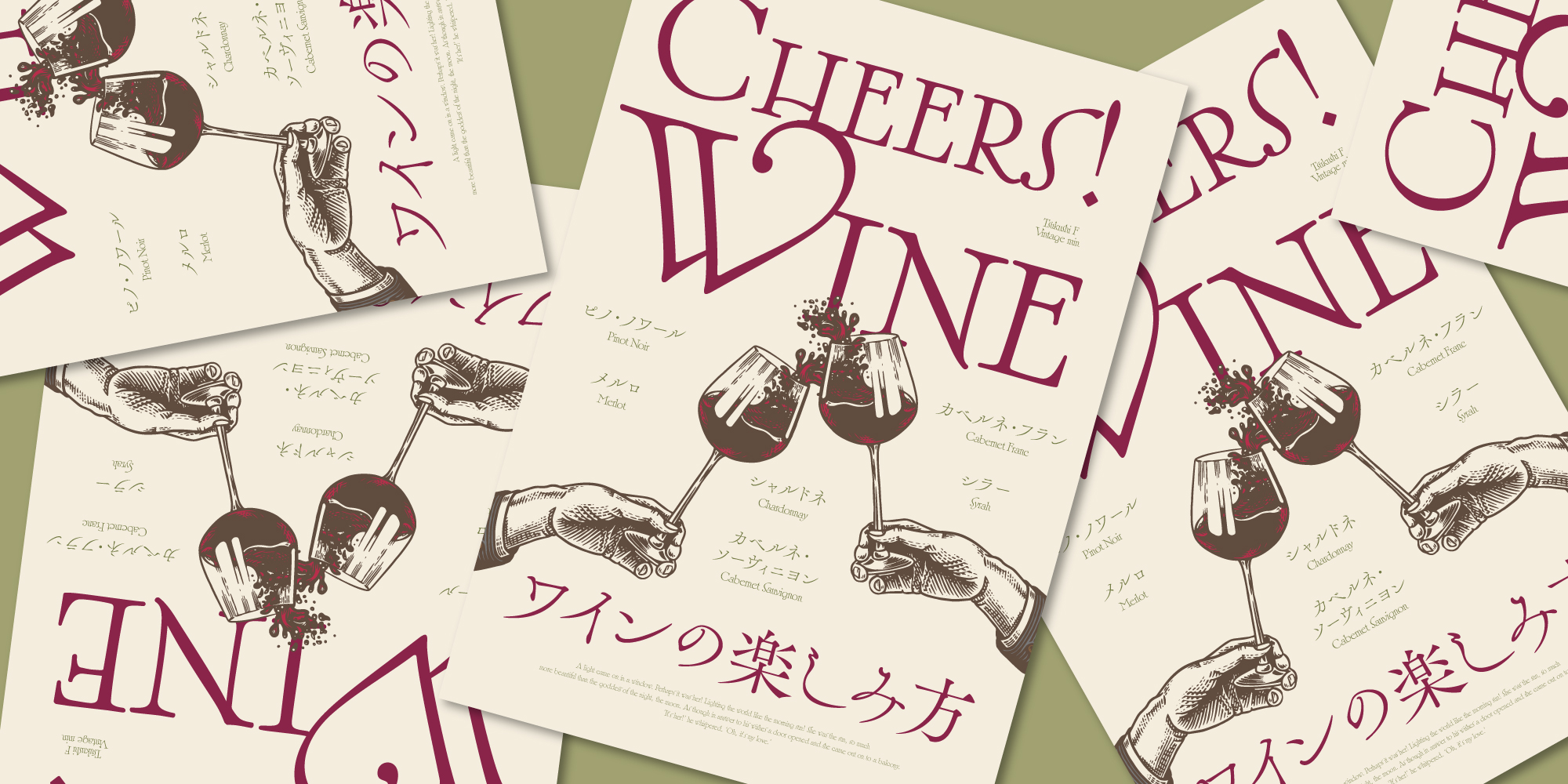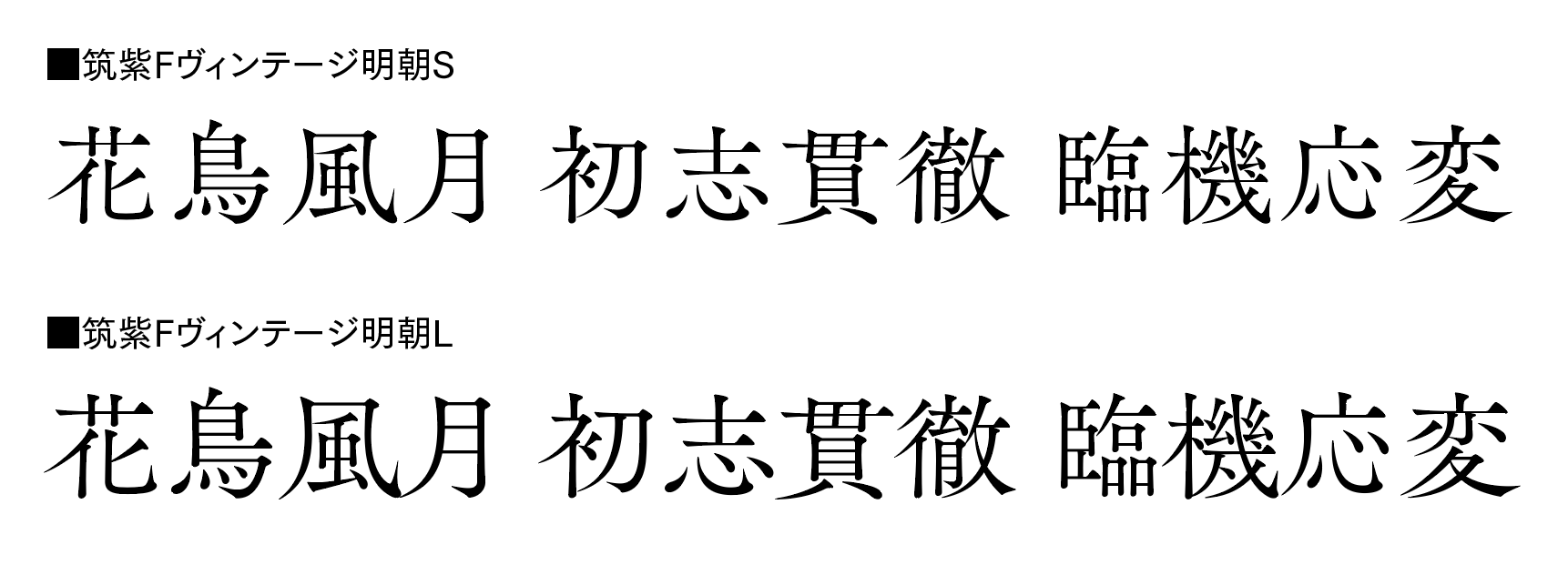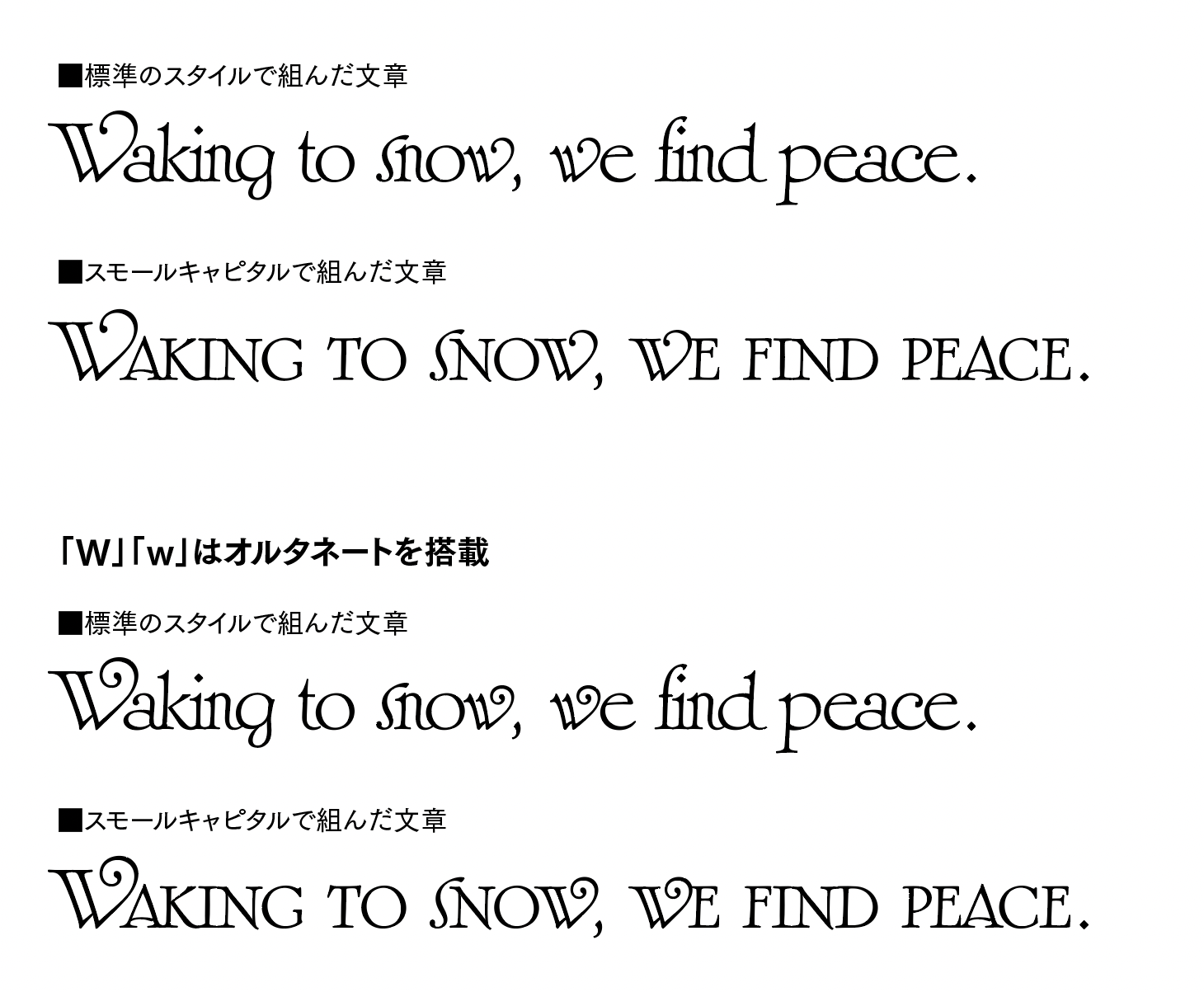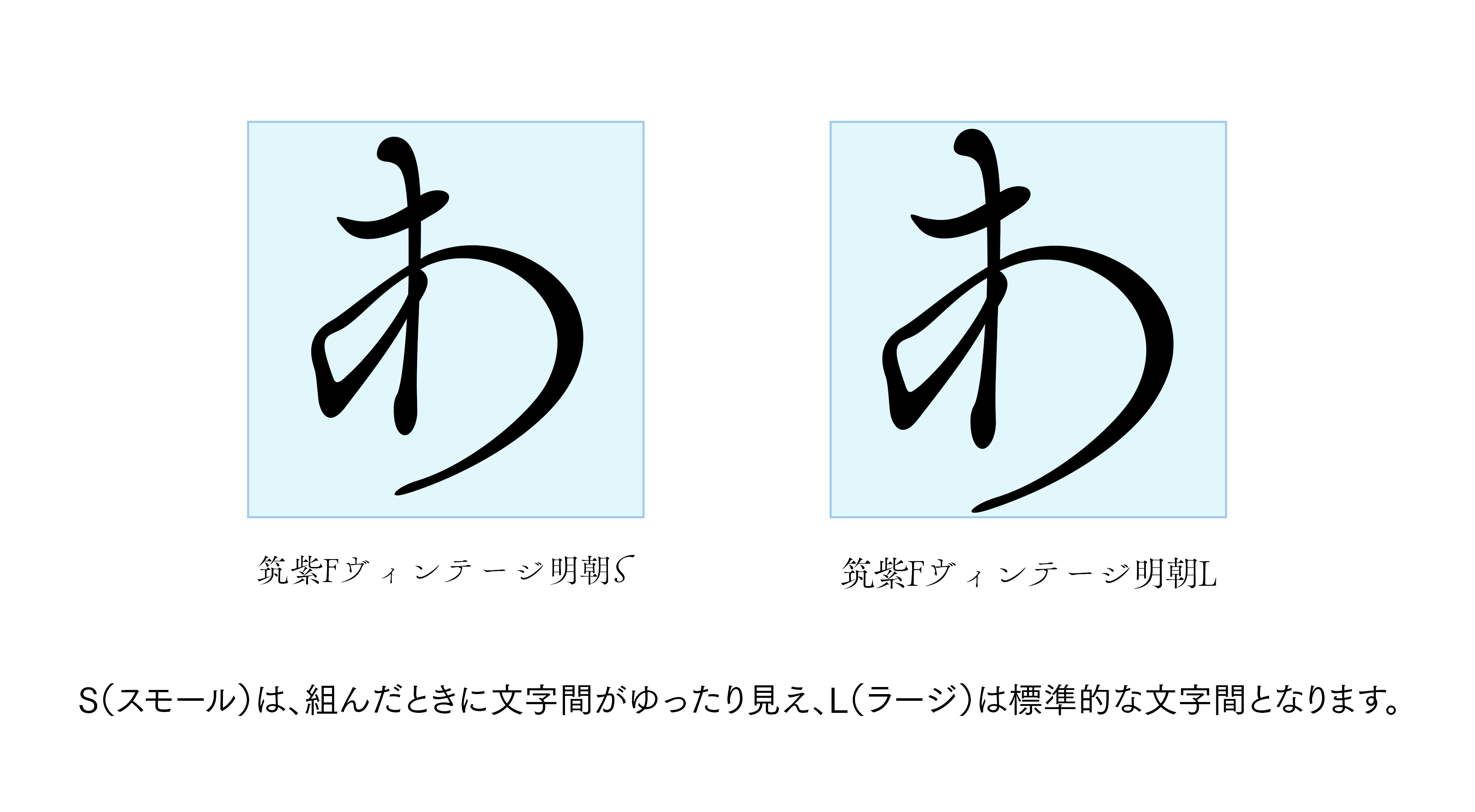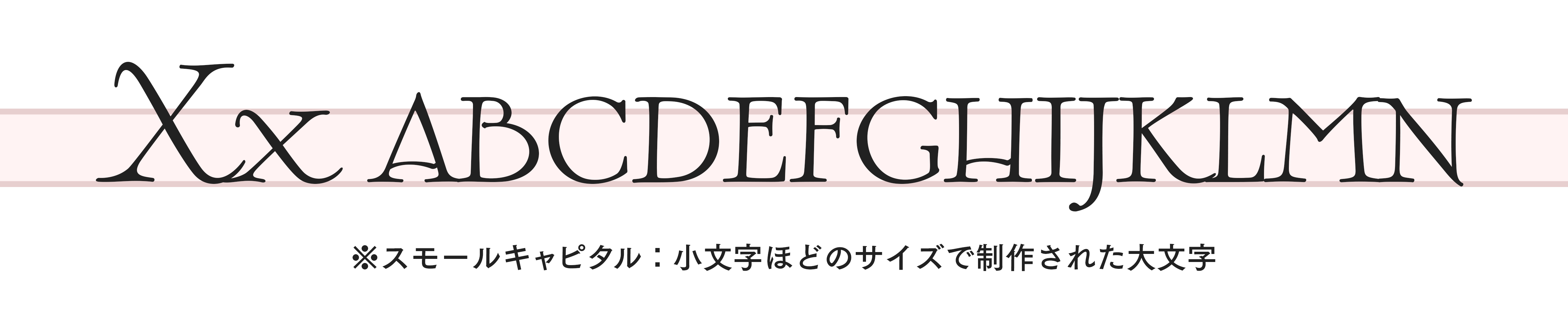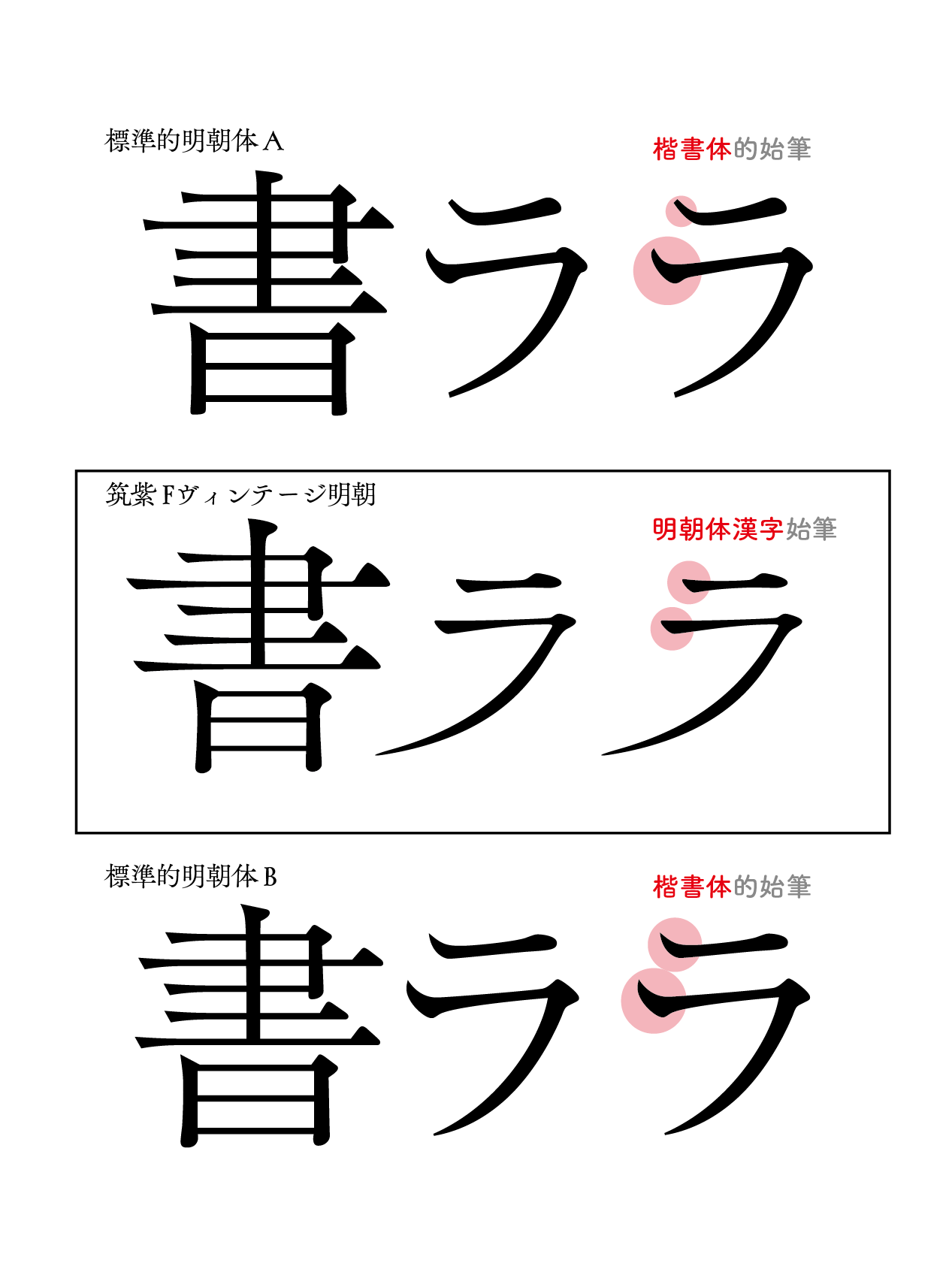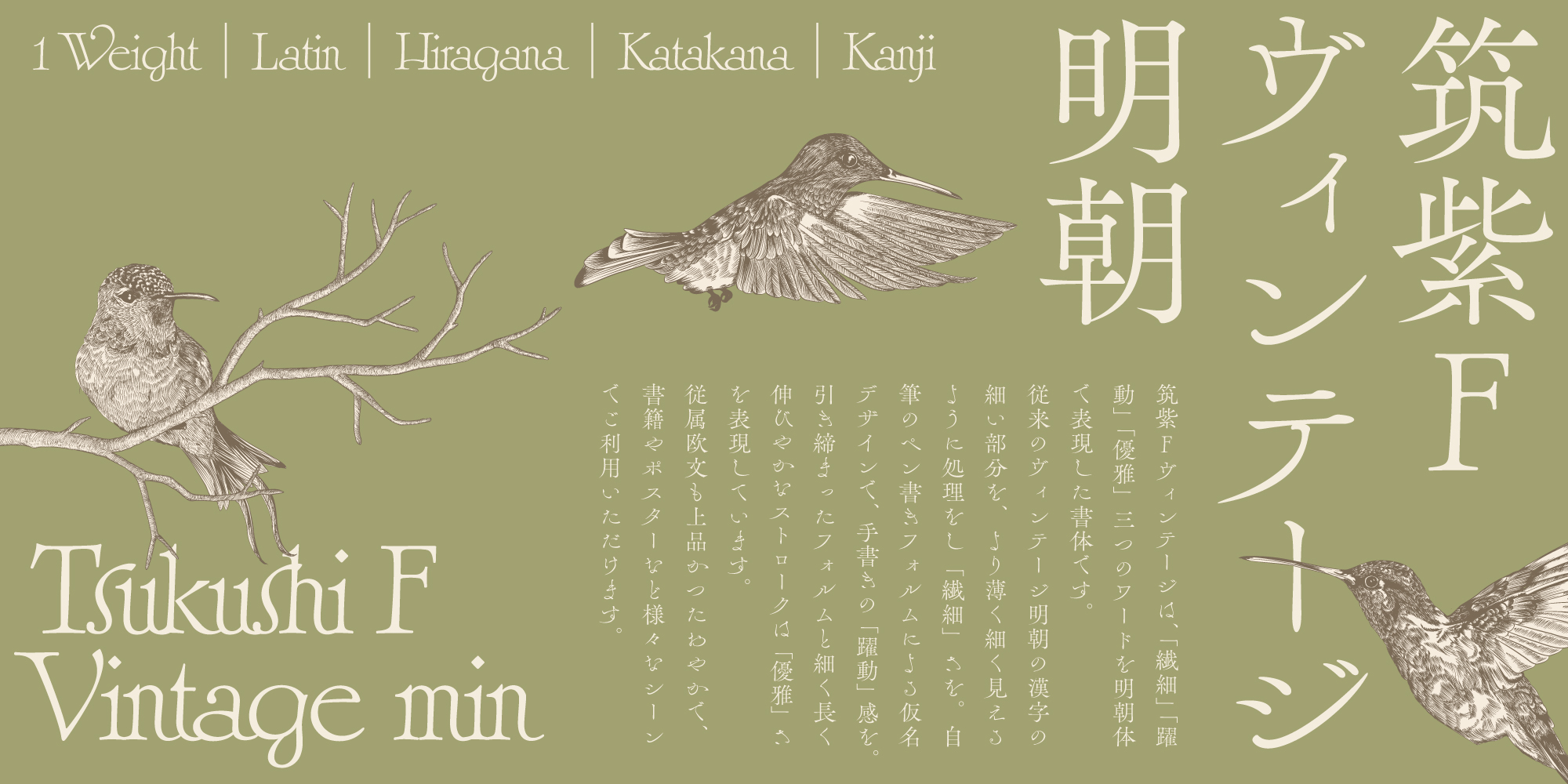
フォントワークス株式会社(本社:東京都港区 代表取締役社長 清水久裕、以下フォントワークス)は、2025年1月22日(水)にフォントワークスの書体デザインディレクター 藤田重信が手掛ける和文書体、フォントワークス 筑紫Fヴィンテージ明朝 RT(Regular Thin)をリリースしました。
また同日に、書籍など幅広いジャンルで人気の和文書体、フォントワークス 筑紫オールドゴシックの新ウエイトL(Light)、EL (Extra Light)も追加されます。
新書体 筑紫Fヴィンテージ明朝について
フォントワークス 筑紫ヴィンテージ明朝シリーズの4書体目となる筑紫Fヴィンテージ明朝は、「繊細」「躍動」「優雅」3つのキーワードをもとにしてできた明朝体です。
従来の筑紫ヴィンテージ明朝の漢字の細い部分をより薄く、細く見えるように処理をし繊細さを表現しています。また、自筆のペン書きフォルムによる仮名デザインで手書きの躍動感を、引き締まったフォルムと細く長く伸びやかなストロークで優雅さを表現しています。文字の大きさの違いにより、S(スモール)とL(ラージ)の2種類があります。
書籍の表紙やポスターなど、様々なシーンでご利用ください。
筑紫ヴィンテージ明朝シリーズ(全4種)
S(スモール)は、組んだときに文字間がゆったり見え、L(ラージ)は標準的な文字間となります。
ユニークさと優雅さを併せ持つカタカナ
カタカナの横画における始筆部が独特な点も筑紫Fヴィンテージ明朝の特長です。スタンダードな明朝体の始筆部は、45度ほどの角度がついているものが多いですが、本書体はそれに比べると滑らかで漢字の横画のような剛直な印象をうけます。文章を組むと、これまでにないユニークな視覚的効果を与えます。また、本書体の魅力である伸びやかなストロークは、カタカナの左ハライでも活きており、制作した書体デザイナー 藤田重信は「筑紫の中でも最も優雅なカタカナです」と語ります。
華やかで優美な付属欧文
筑紫Fヴィンテージ明朝の付属欧文は華やかな優美さが特長です。「W」「w」の2文字は巻きが強いオルタネート(異字体)を搭載。用途に応じての使い分けが可能です。
また本書体の付属欧文は、イタリック体収容部分にスモールキャピタル※を収録しています。
筑紫オールドゴシック、新たに2ウエイト追加
同日、フォントワークス 筑紫オールドゴシックに新たにEL (Extra Light)とL(Light)の2ウエイトが追加されます。
筑紫オールドゴシックは、藤田重信が2014年に、金属活字時代に存在していたかのようなゴシック体をイメージしながら設計した、全く新しい書体です。漢字や仮名の引き締まったふところ、伸びやかなハライ、筆の名残りを感じる豊かな抑揚が、凜々しく言葉を語ります。
2024年9月にリリースしたR(Regular)、M (Medium)、D(Demi Bold)、E(Extra)に続き、今回EL、Lが追加され、全8ウエイトを持つファミリーとなりました。